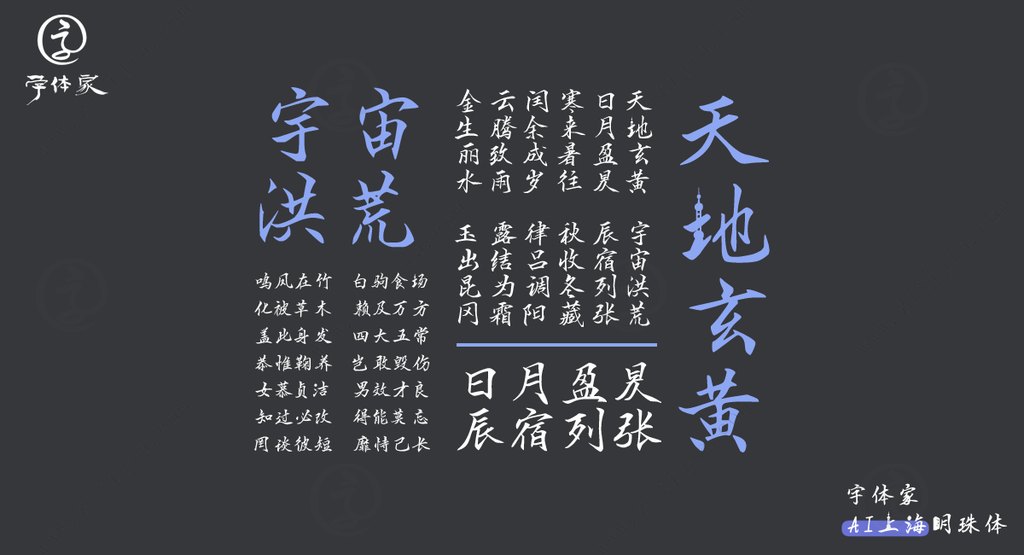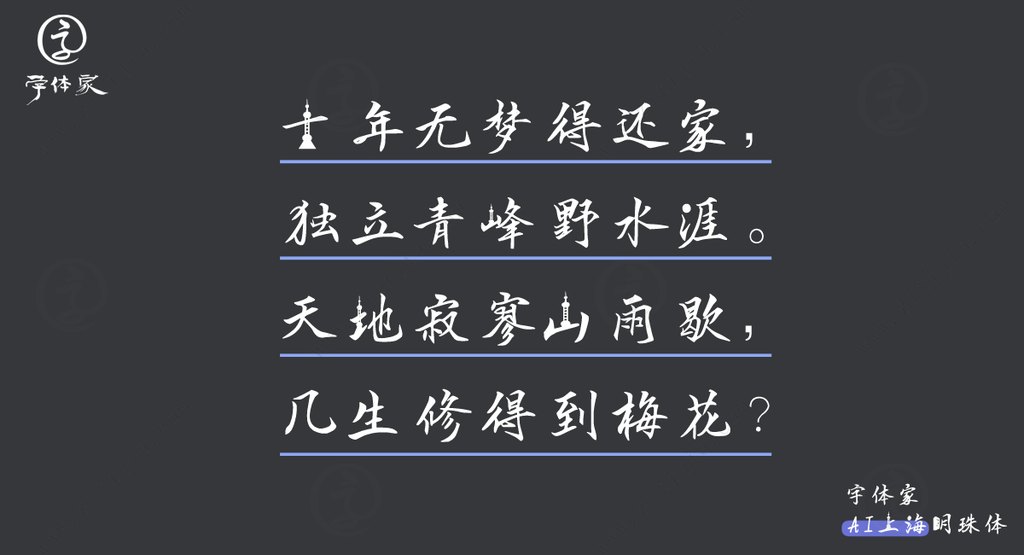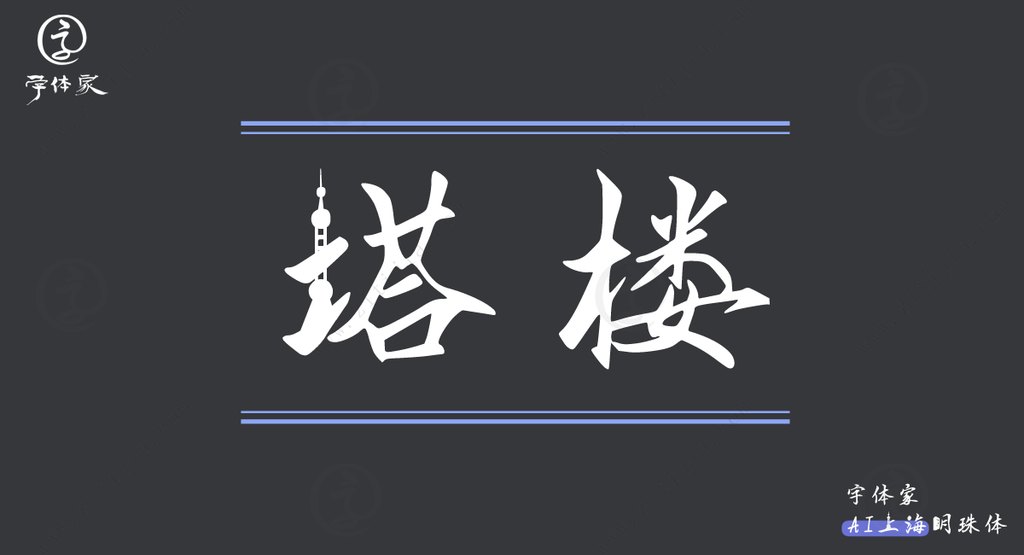
字体家AI上海明珠体:现代艺术与城市灵魂的完美碰撞
大家好,今天我带来了一款让我激动不已的新字体——字体家AI上海明珠体。它不仅仅是我们日常看到的楷书,而是将现代艺术与上海这座辉煌城市的特色完美结合。准备好迎接你的视觉盛宴了吗?
上海明珠体的创意来自于字体家AI的神笔造字技术,它通过精准的计算和独特的设计,将“东方明珠塔”和高楼的造型巧妙地融入到传统书法字体中。结果如何?一个字:惊艳。
这一款字体的魅力在于它既保留了楷书的精致特质,又赋予了每一个字现代都市的活力。这样一来,字体不仅传递了美学的享受,还让文字充满了上海的城市气息——一个既传统又现代的双重体验。
无论是广告标题、平面文案、还是网页广告,上海明珠体都能轻而易举地抓住观众的眼球。它的应用场景也十分广泛,适合用于需要强调视觉冲击力的任何设计项目。
在我看来,上海明珠体不仅仅是一款字体,它更是一座桥梁,将我们从繁忙的每日生活中带到这座城市的灵魂之中。它让我们感受到上海的精致、现代和时髦。
所以,下次你在设计广告或者海报时,试试这款独特的字体吧。相信我,它一定会让你和你的观众耳目一新。上海明珠体,将城市艺术融入你的创意世界!